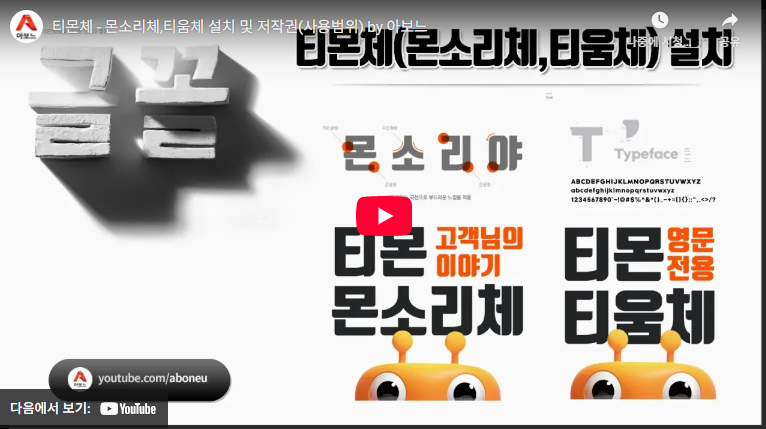
티몬체(구 몬소리체)는 티몬에서 개발한 무료 서체로, 부드러운 곡선과 강렬한 굵기를 갖춘 독창적인 글꼴입니다. 다운로드 및 설치 방법, 활용 가능한 디자인 영역, TTF·OTF 파일 특징, 저작권 정보와 추천 이유까지 자세히 정리했습니다. 포스터·배너 적용 팁도 함께 안내합니다.
1. 티몬체 소개
티몬체는 티켓몬스터(TMON)에서 개발한 무료 서체로, 처음에는 ‘몬소리체’라는 이름으로 출시되었다가 이후 이름이 변경되었습니다. 굵고 안정적인 가독성, 부드러운 곡선 덕분에 광고·웹디자인·포스터 등 다양한 분야에서 활용됩니다. 브랜드 아이덴티티 강화와 시각적 커뮤니케이션에 유용한 글꼴입니다.
3. 티몬체 디자인 특징
티몬체는 부드러운 곡선과 임팩트 있는 굵기가 조화를 이루어 시선을 끌면서도 피로감이 적습니다. 고딕체가 주는 딱딱함 대신 유연하고 개성 있는 느낌을 제공해 광고나 발표 자료에서 효과적입니다.
4. 활용 가능 영역
| 활용 분야 | 설명 |
|---|---|
| 인쇄물 | 포스터, 잡지, 출판물 |
| 디지털 디자인 | 웹페이지, 배너, 메일 |
| 영상 작업 | 자막, 영화 크레딧 |
| 브랜드 작업 | 회사명, 상품명, BI/CI |
7. 추천 이유
티몬체는 가독성과 개성을 동시에 갖춘 서체로, 많은 디자이너들이 애용합니다. 부드러우면서도 힘 있는 인상을 줄 수 있어 시각적 강조가 필요한 프로젝트에 특히 적합합니다. 무료 배포임에도 상업적 활용이 가능하다는 점도 큰 장점입니다.